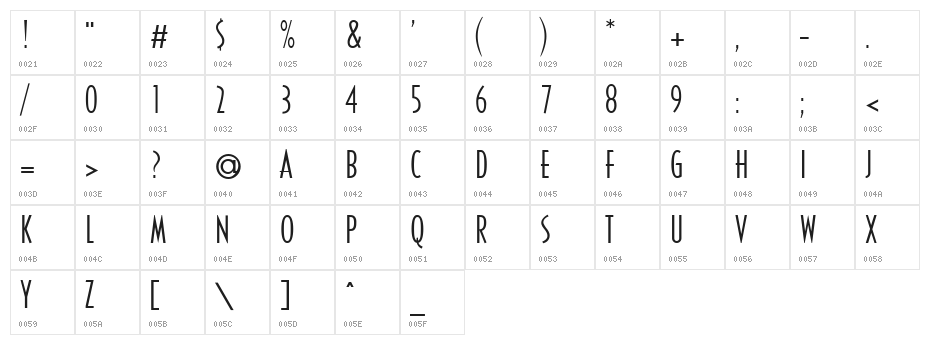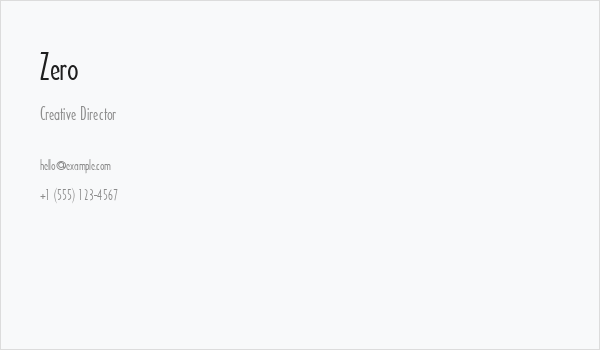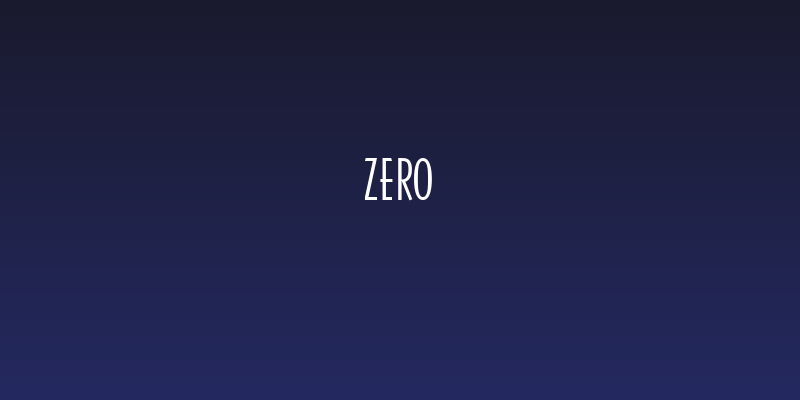
Zero Font
| Kategorien | Sans Serif |
| Anwendungsfall | Headlines, Logos, Digital interfaces |
| Vorgeschlagene Projekte | Ideal for branding, editorial design, advertising, and digital interfaces where a modern and sophisticated look is desired. |